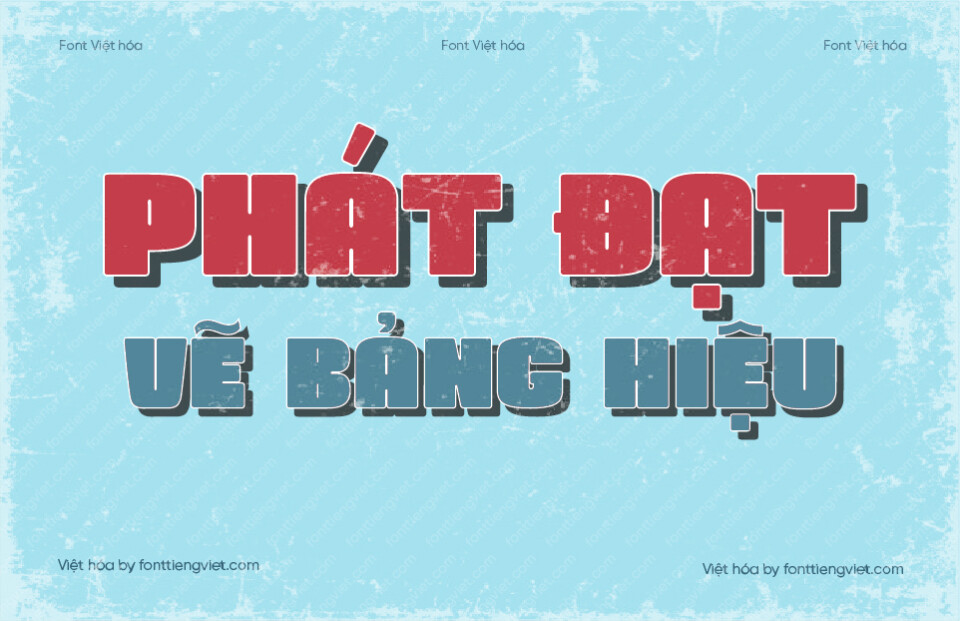
Tải Font Việt hóa 1FTV VIP Tarragon – Bộ Font Chữ Sang Trọng Cho Thiết Kế Giáo Dục
Giới thiệu về Font Việt hóa 1FTV VIP Tarragon
Trong thế giới thiết kế đồ họa hiện đại, việc lựa chọn một bộ Font Chữ phù hợp đóng vai trò quan trọng trong việc truyền tải thông điệp. Font Việt hóa 1FTV VIP Tarragon là một tác phẩm nghệ thuật chữ viết đầy ấn tượng, kết hợp hài hòa giữa nét cổ điển và hơi thở đương đại. Đây là lựa chọn lý tưởng cho các bạn học sinh và giáo viên muốn làm mới các bài thuyết trình hay tài liệu học tập. Với các đường nét thanh thoát nhưng không kém phần mạnh mẽ, bộ font này giúp mọi văn bản trở nên chuyên nghiệp và thu hút hơn ngay từ cái nhìn đầu tiên.
Đặc điểm nổi bật của Font Việt hóa 1FTV VIP Tarragon
Thiết kế tinh tế và tính ứng dụng cao
Bộ Font Việt hóa 1FTV VIP Tarragon nổi bật với cấu trúc ký tự cân đối, dễ đọc trên cả thiết kế in ấn lẫn hiển thị kỹ thuật số. Điểm đặc biệt của phiên bản này là đã được tối ưu hóa đầy đủ các dấu tiếng Việt, giúp người dùng không còn lo lắng về lỗi hiển thị ký tự khi soạn thảo văn bản. Các bạn học sinh có thể sử dụng font này để thiết kế bìa báo tường, làm thiệp chúc mừng thầy cô hoặc trang trí slide bài giảng. Sự linh hoạt của Tarragon cho phép nó tỏa sáng trong nhiều bối cảnh khác nhau, từ tiêu đề trang trọng đến các đoạn trích dẫn đầy cảm hứng trong môi trường học đường.
Lời kết về bộ font độc đáo này
Hy vọng rằng bộ Font Việt hóa 1FTV VIP Tarragon sẽ trở thành nguồn cảm hứng mới cho các dự án sáng tạo của bạn. Sự kết hợp giữa vẻ đẹp thẩm mỹ và công năng sử dụng vượt trội chắc chắn sẽ làm hài lòng những người dùng khó tính nhất. Hãy trải nghiệm ngay bộ Font Miễn Phí, Font Việt Hóa, Font Việt hóa 1FTV VIP Tarragon để nâng tầm chất lượng cho các bản thiết kế của mình ngay hôm nay bạn nhé.